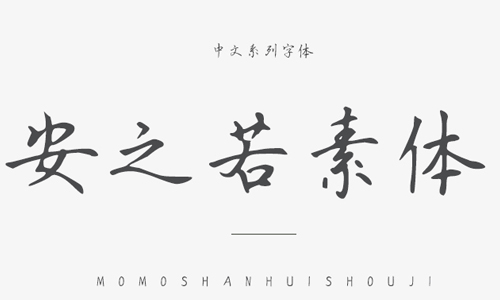
安之若素體字體是一款非常漂亮的硬筆手寫風(fēng)格字體,很有楷書字體和隸書書法字體的運(yùn)維,給人干凈簡潔的娟秀之美,讓文字更有質(zhì)感和藝術(shù)效果,使用范圍較廣,能夠應(yīng)用于文本裝潢、信息展示、網(wǎng)頁設(shè)計、篆刻制模、數(shù)據(jù)制作、裝潢設(shè)計、計算藝術(shù)設(shè)計、視覺設(shè)計、字帖等一切合法應(yīng)用場景,歡迎有需要的朋友前來下載使用。
“繁華盡處,尋一處無人山谷,建一木制小屋,鋪一青石小路,與你晨鐘暮鼓,安之若素。”——安之若素體。
本字體是在國家標(biāo)準(zhǔn)簡體字庫GB2312所包含6763漢字的基礎(chǔ)上,又增加了近200常用字,已經(jīng)覆蓋了大陸99.75%的漢字使用頻率,足以滿足日常需求。